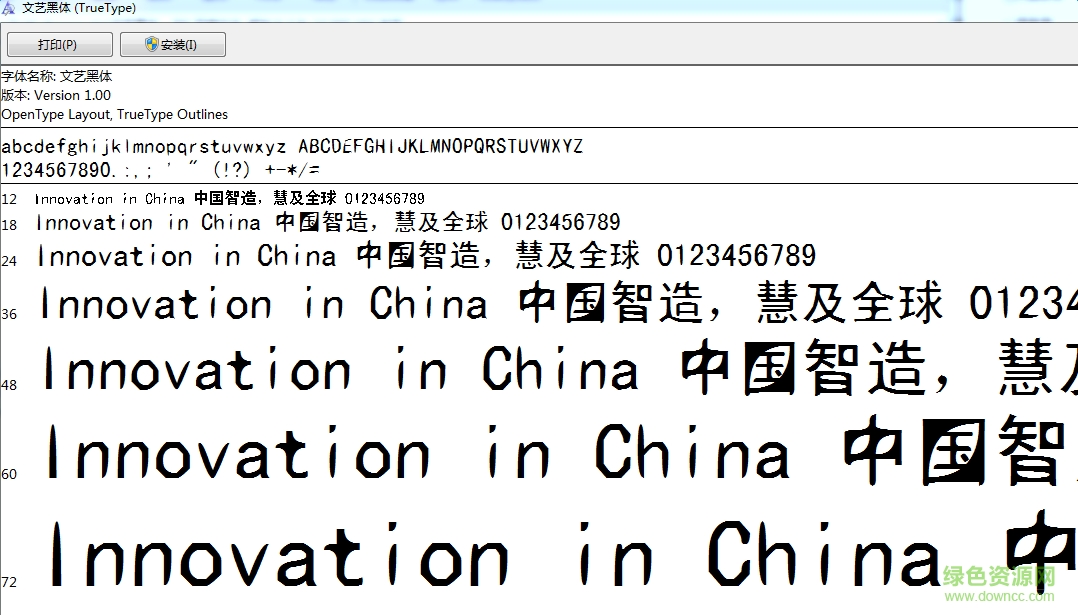
文藝青年字體是一款充滿文藝氣息的伯樂(lè)字體,簡(jiǎn)約端正有摻雜著藝術(shù)氣息,字跡辨識(shí)度搞,有著舒適的視覺(jué)呈現(xiàn),喜歡的朋友千萬(wàn)不要錯(cuò)過(guò),綠色資源網(wǎng)即可滿足你!
文藝青年字體作為伯樂(lè)字體即將推出的藝術(shù)字體,以文藝風(fēng)范為主打,滿足了各類文藝青年和少女們的喜好,字跡簡(jiǎn)約端正,時(shí)尚中帶點(diǎn)頹靡,昂揚(yáng)中帶點(diǎn)不羈,很有獨(dú)特魅力。